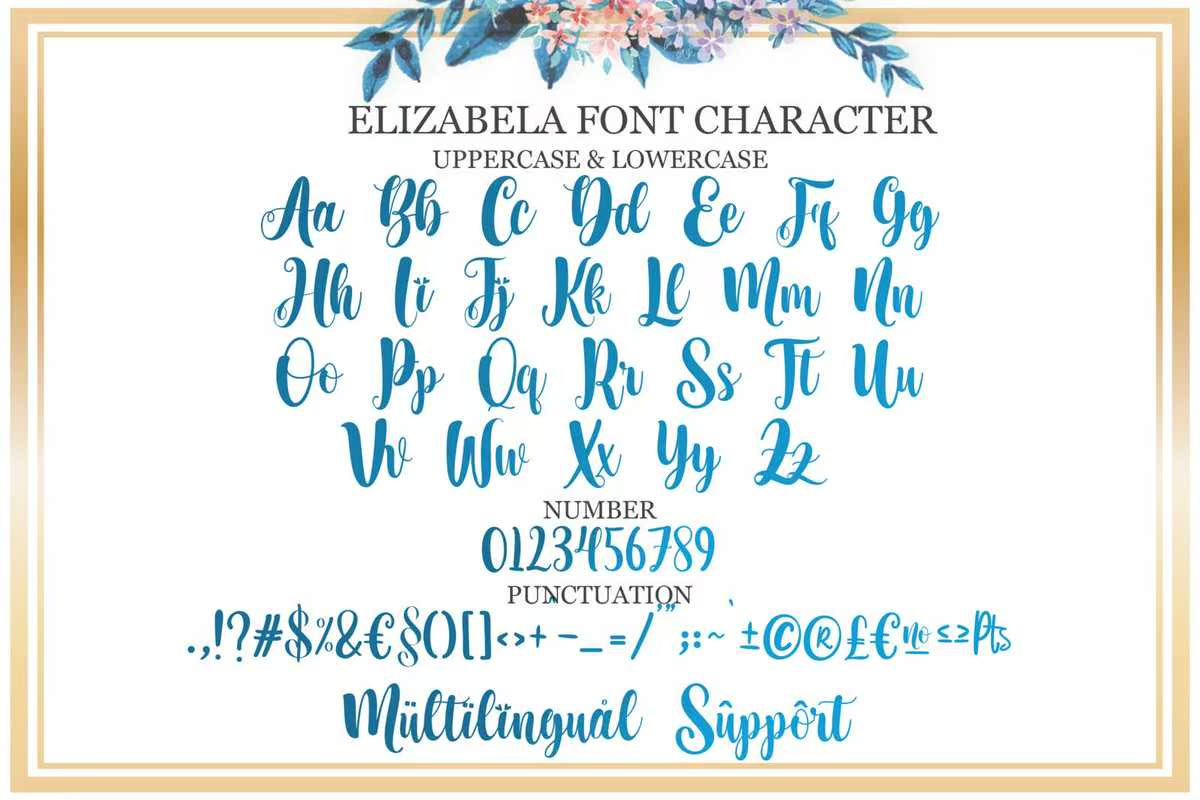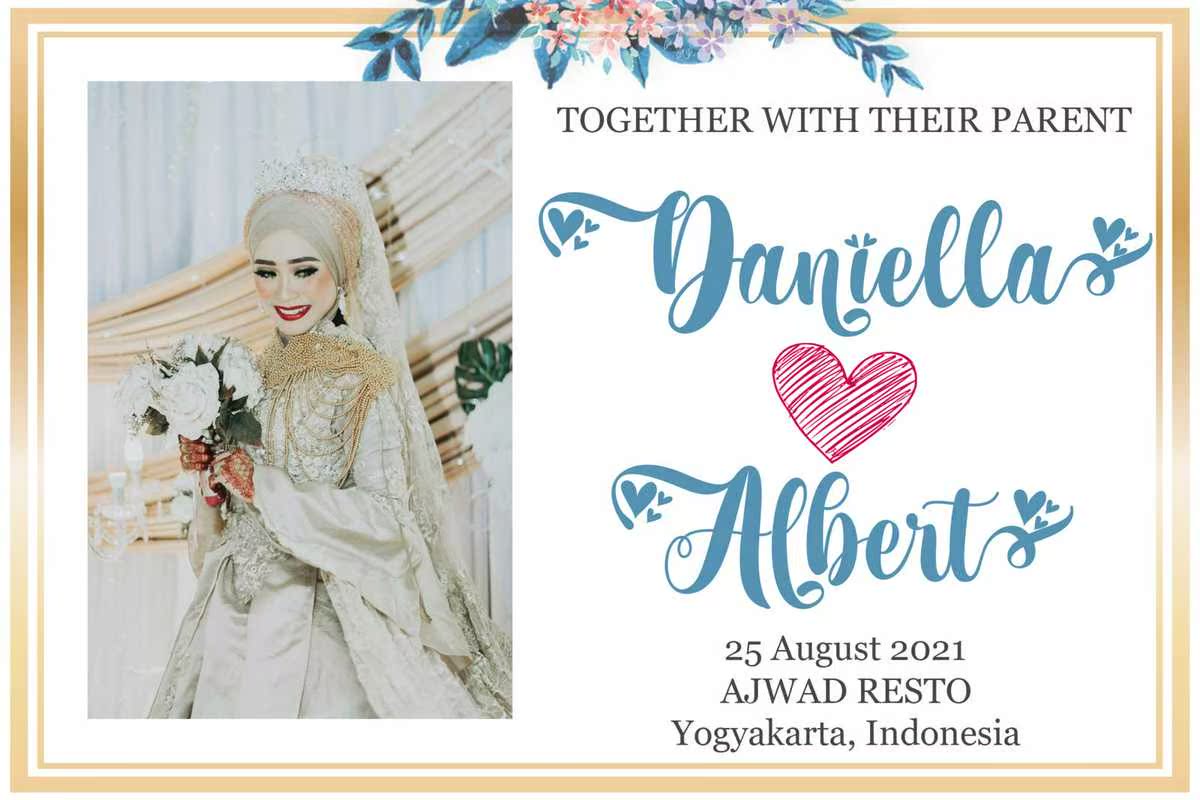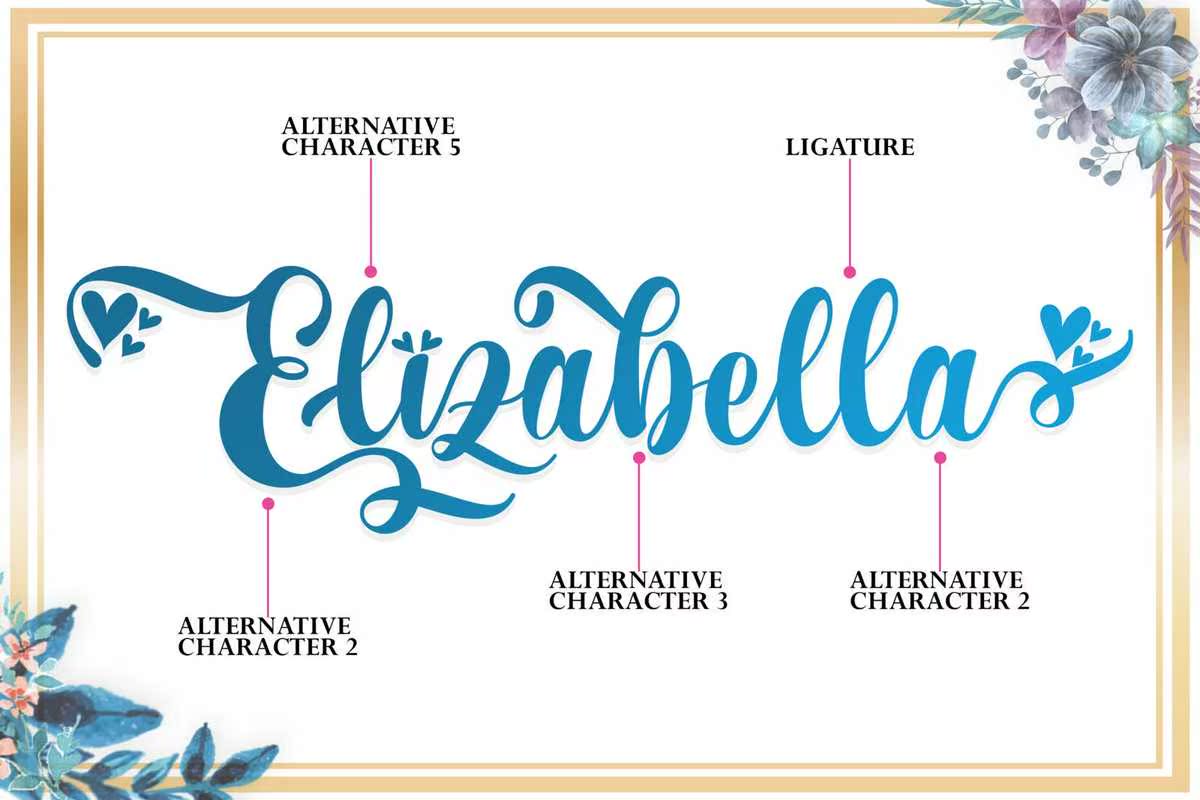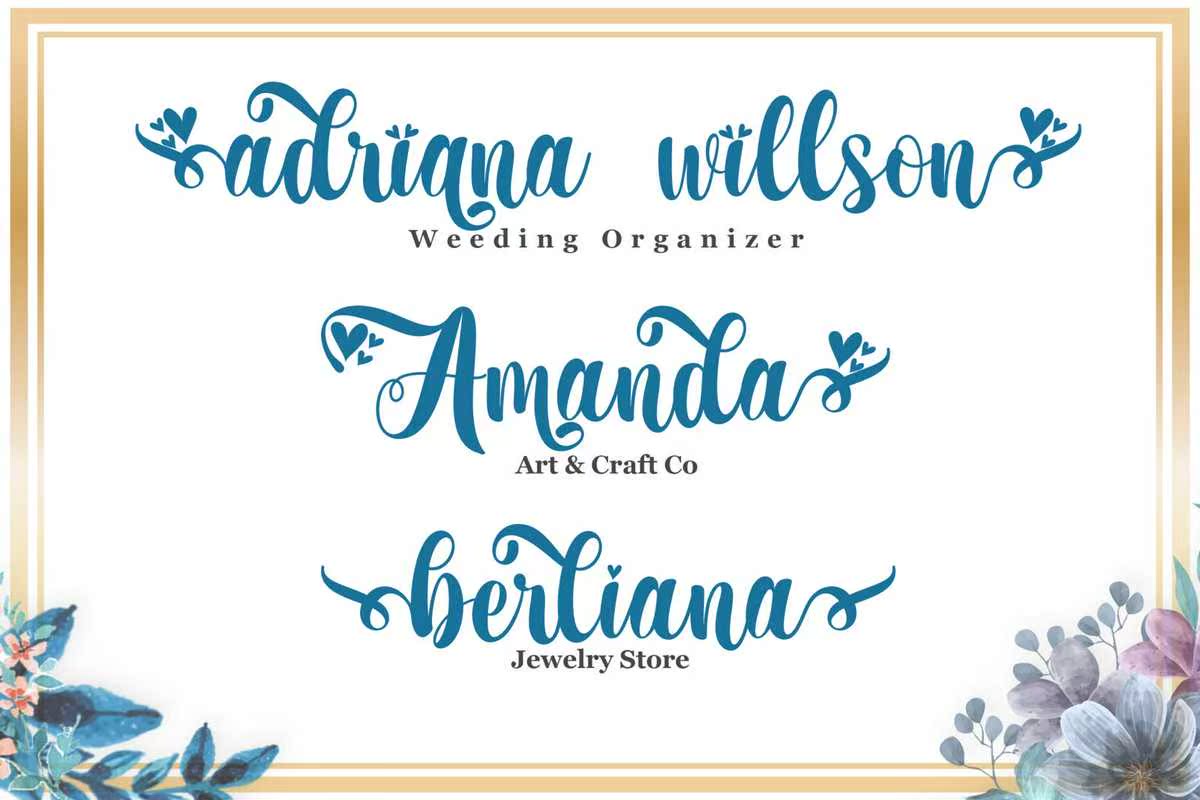
HiGuys.我们从我们的研究中引进了我们的新产品“Elizabella”。Elizabella是一种现代书法脚本字体,在字形中带有“爱”的口音。这种字体非常适合您的设计项目,如eBanner、海报、邀请、,等。我希望你能喜欢这个字体。我们从我们的研究中引进了我们公司的产品“Elizabella”。Elizabella是一种现代书法脚本字体,在字形中非常强调“爱”。这个字体非常适合你的设计项目,如班纳、海报、邀请函等。我希望你能喜欢这个字体